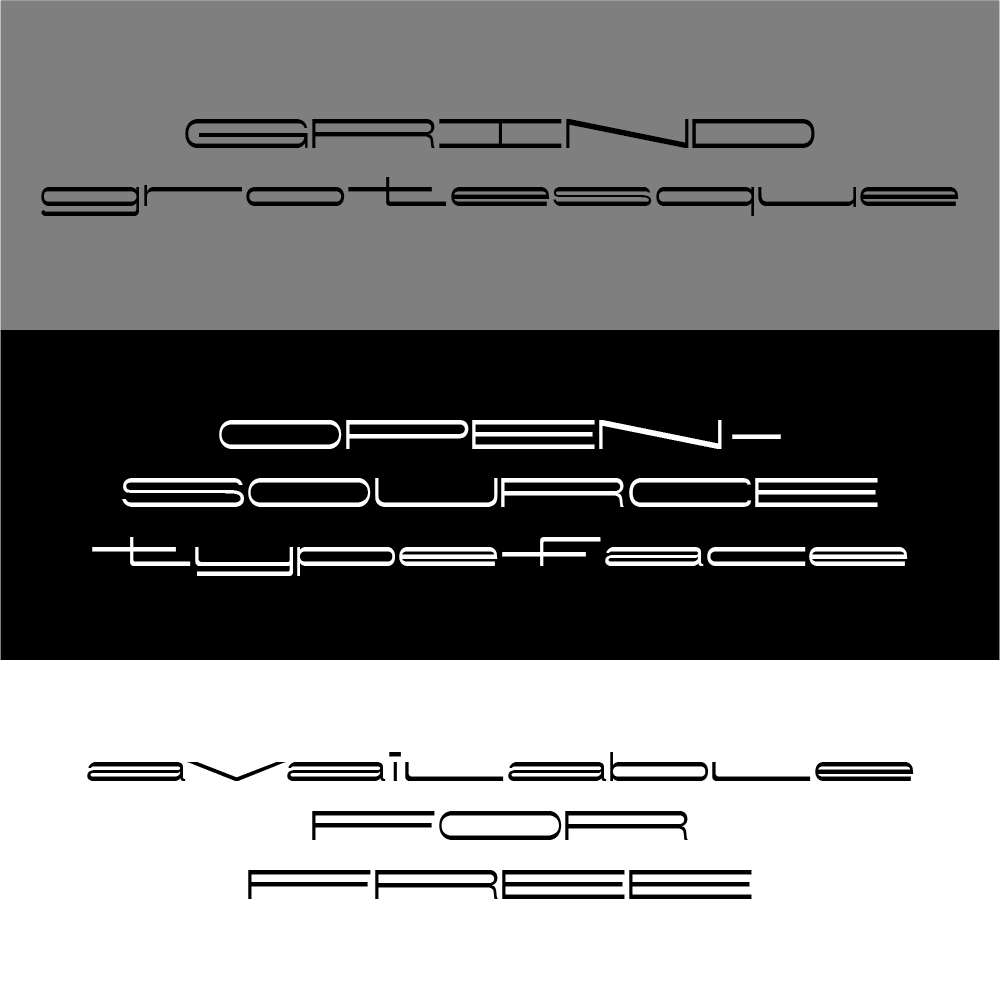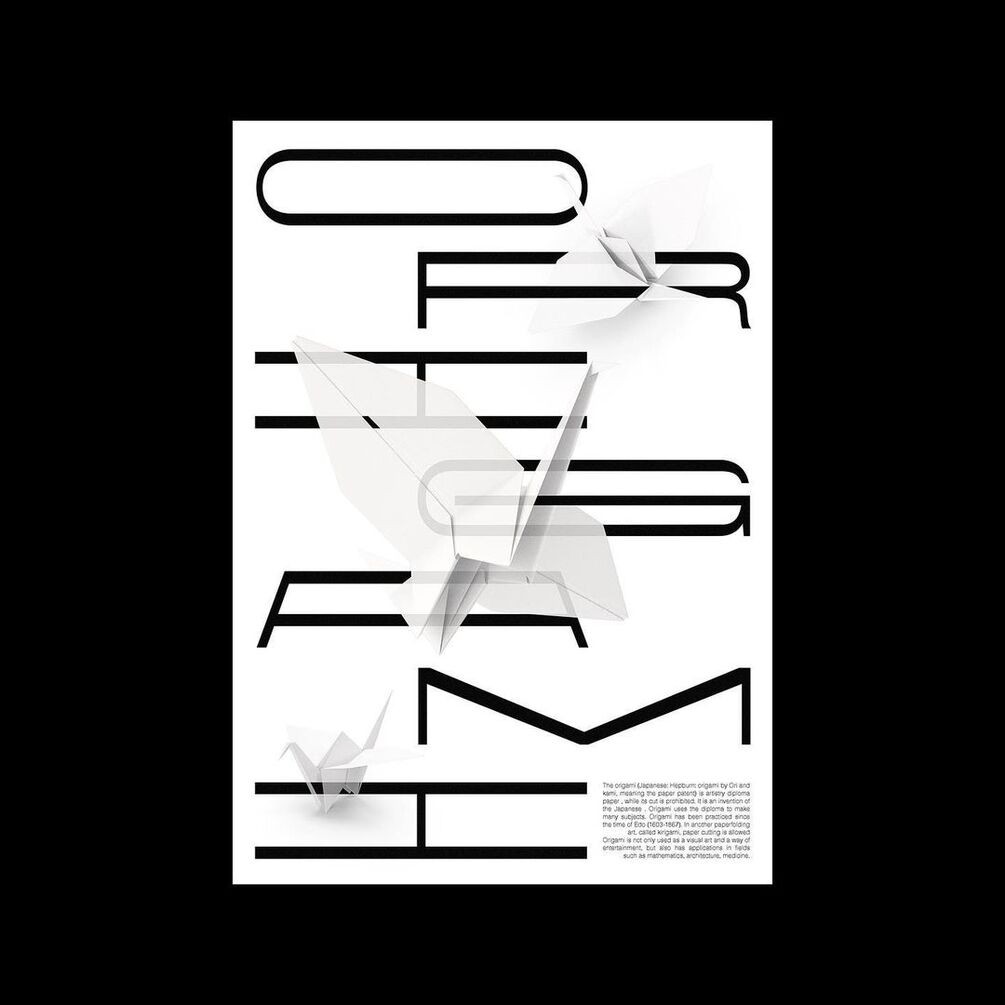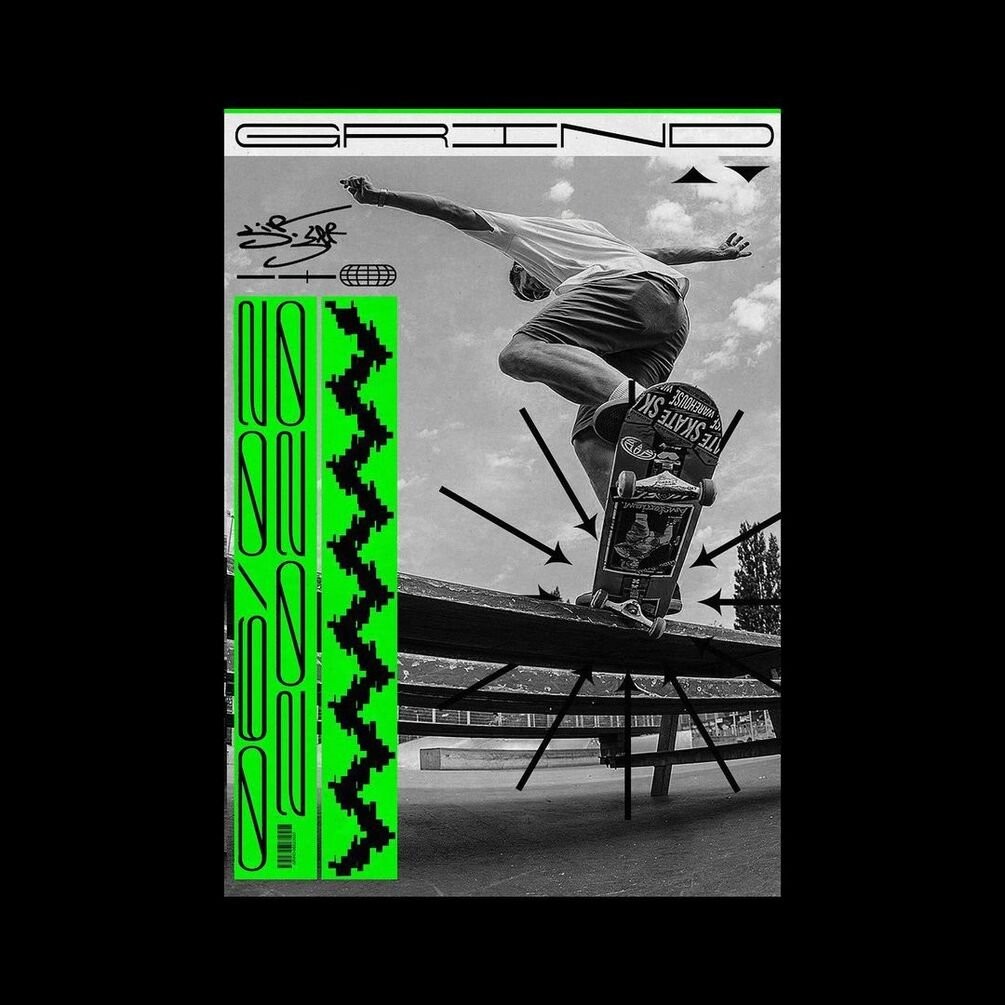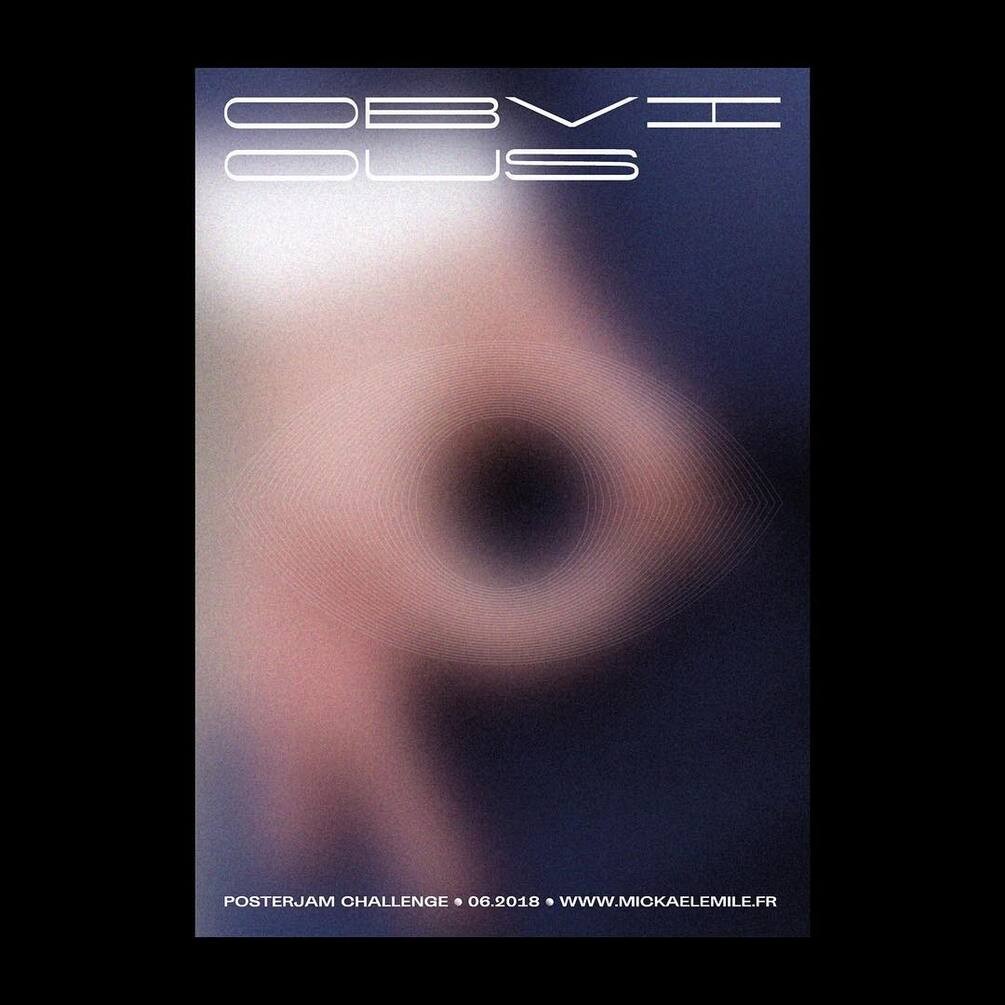
Grind Grotesque现代英文宽字体,免费可商用
一款适用于现代设计的字体,其简洁、醒目和易读的特点使其成为许多设计师和创意人士的首选。它适用于标志设计、海报、包装设计、网页设计等各种应用场景,为您的设计作品带来现代感和独特的风格。Grind Grotesque字体支持OFL开源协议,可用于个人和商业用途。